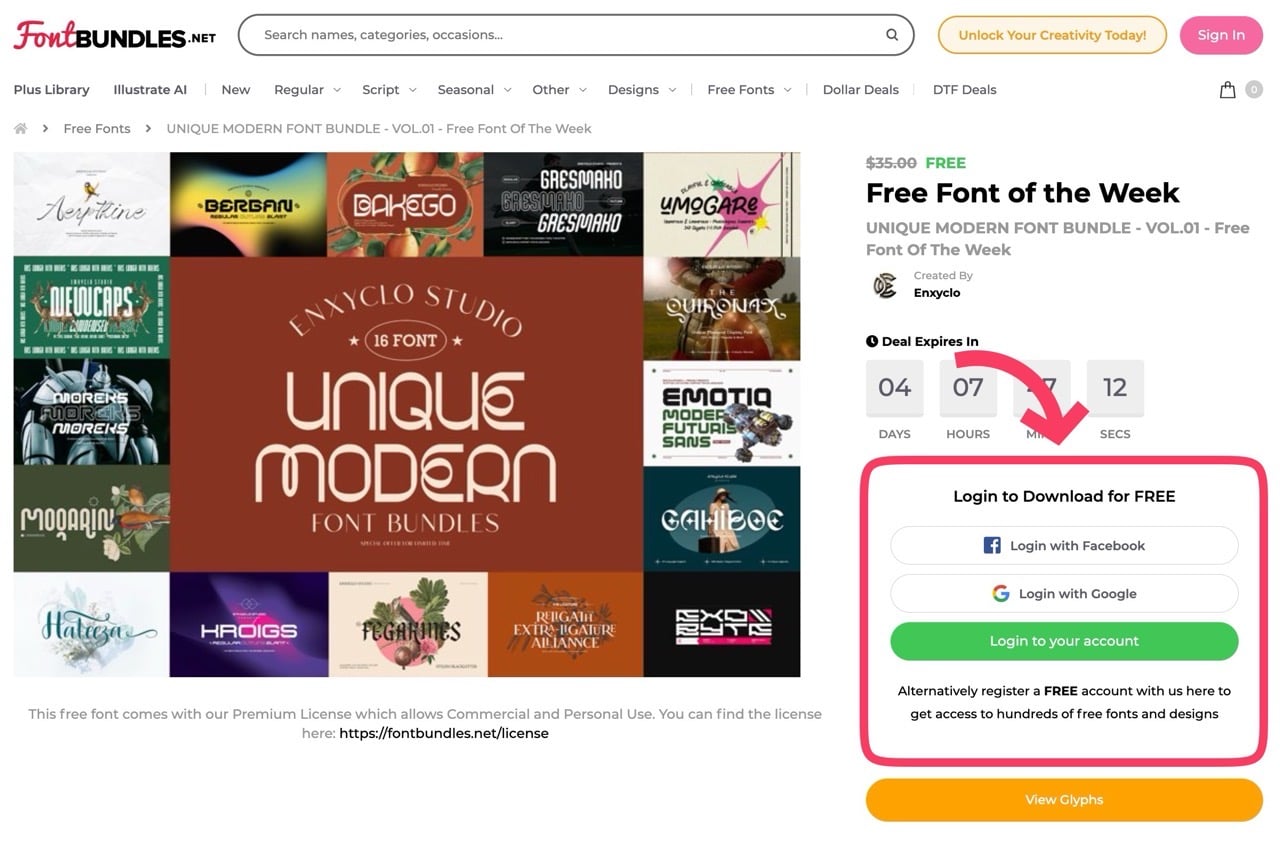
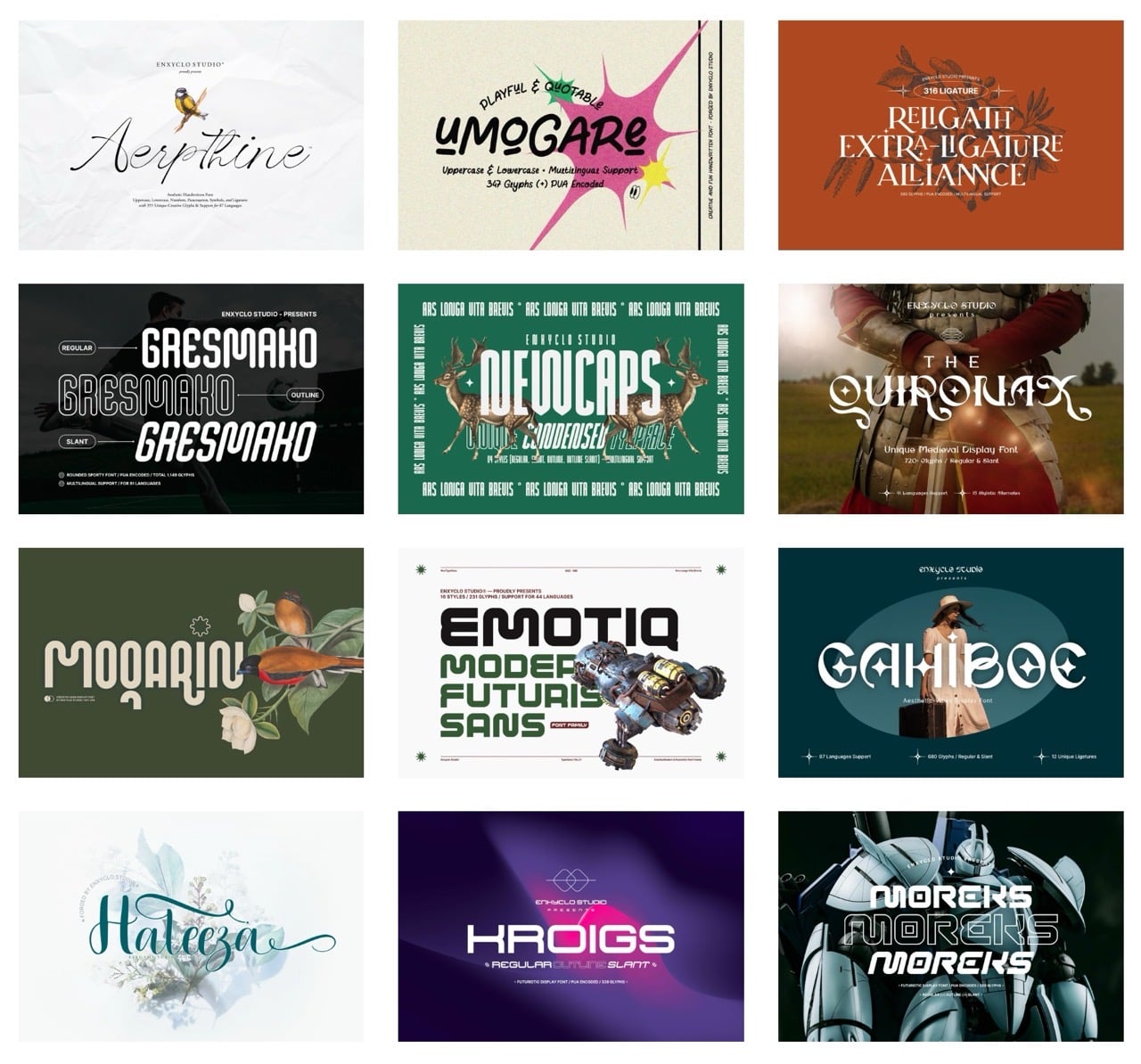
UNIQUE MODERN FONT BUNDLE 系列特色
這次的主題是「UNIQUE MODERN FONT BUNDLE – VOL.01」獨特現代風格字體包,由設計師 Enxyclo 開發製作,原價為 $35 美元,一共收錄 16 種字型,這些字體營造一種時尚、精緻且極具當代感的視覺風格,具有強烈吸引力,使用在設計上可以馬上抓住瀏覽者的目光。